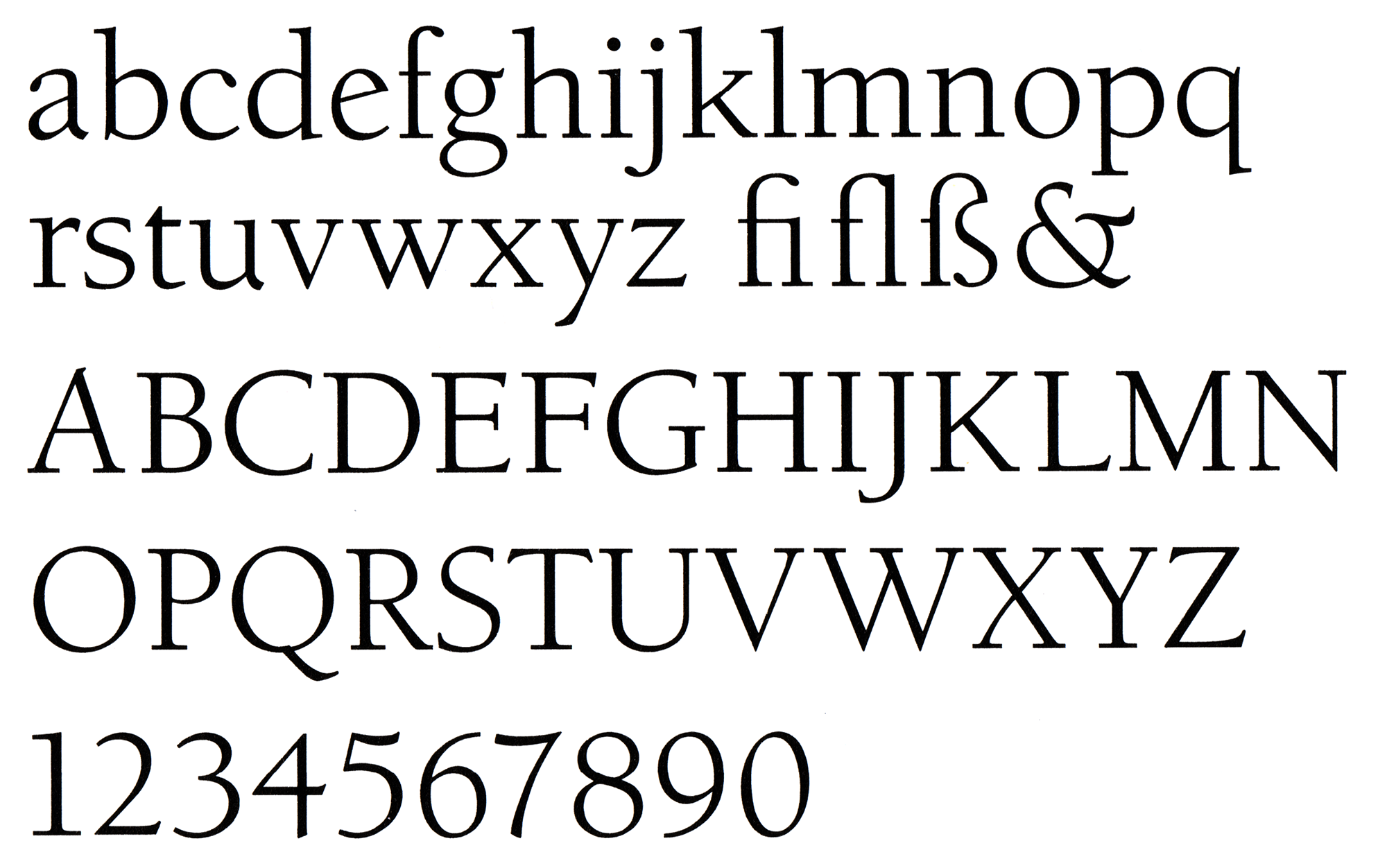
Font-Wiki: ITC Berkeley Old Style
Die ITC Berkeley Old Style wurde von Tony Stan für die International Typeface Corporation geschaffen. Ihre Gestaltung basiert auf einer von Frederic Goudy 1938 entworfenen Exklusivschrift für die University of California. Diese war auch die Vorlage für die FB Californian, die David Berlow 1990 herausbrachte. Berlows Variante bewahrt aber deutlich mehr Details der Ursprungsschrift, während die Berkeley Old Style eine freiere, etwas glattere und plakativere Interpretation des Originals ist. Ins Auge fallen zarte Details wie das kleine Häkchen am kursiven e, die das elegante und warme Erscheinungsbild der Berkeley prägen.